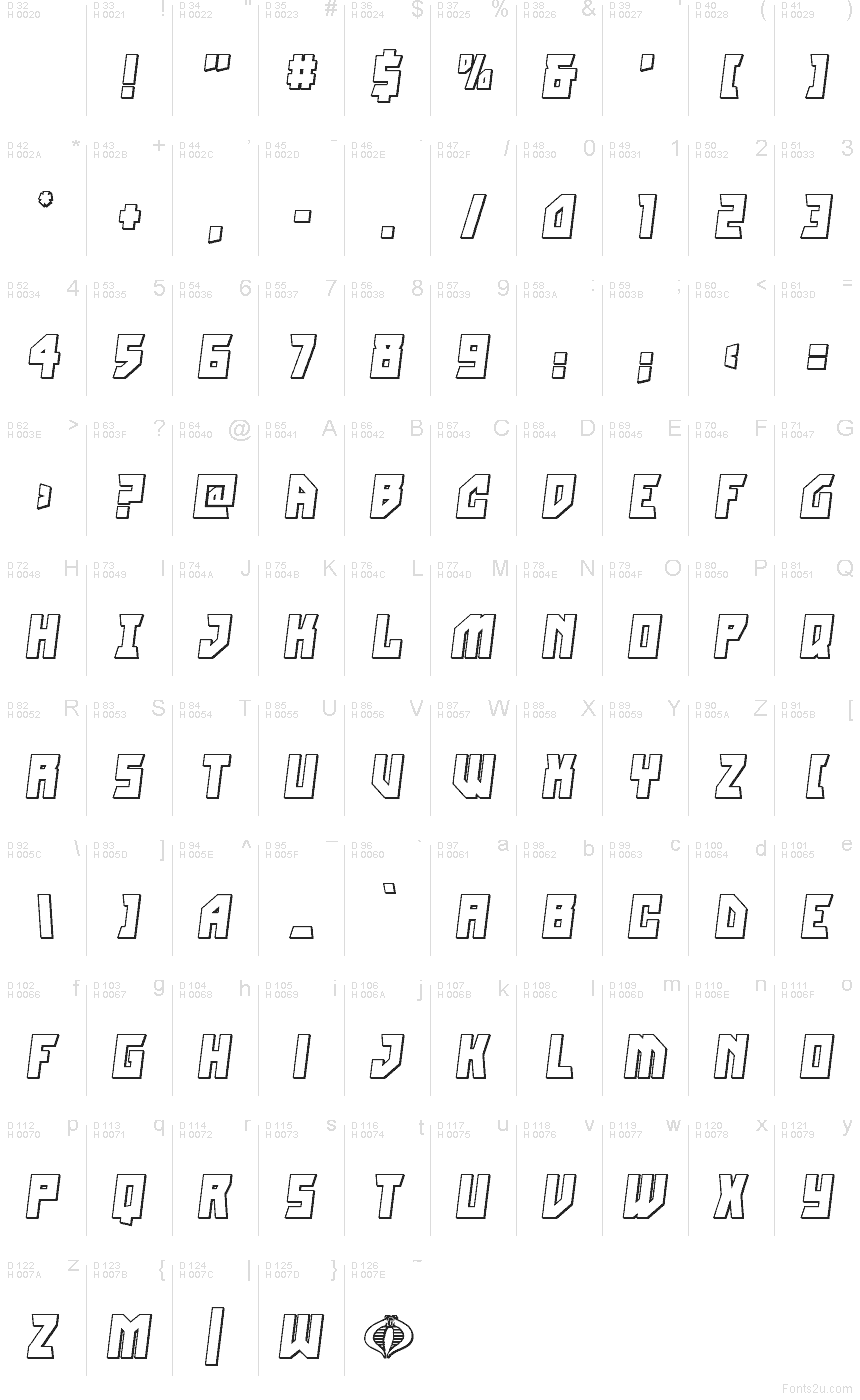
Omni-cobra 3D
Omni-cobra 3D de Iconian Fonts es una tipografía 3D futurista gratuita, ideal para titulares, que destaca por sus formas angulares, contornos afilados y una sombra escalonada que aporta a cada letra un acabado mecánico y superpuesto. Sus recortes internos estrechos y sus lados inclinados dotan al diseño de una estética rígida y gráfica, mientras que su marcada extrusión genera una gran sensación de profundidad.
Omni-cobra 3D funciona a la perfección en pósteres de ciencia ficción, logotipos de videojuegos, branding de salas recreativas, flyers de eventos y packaging de temática de acción, ya que sus formas facetadas parecen letras talladas en metal o moldeadas en plástico. Esta fuente gratuita también es ideal para banners, arte de álbumes y tratamientos de títulos cuando buscas un estilo contundente con un impacto tridimensional definido.